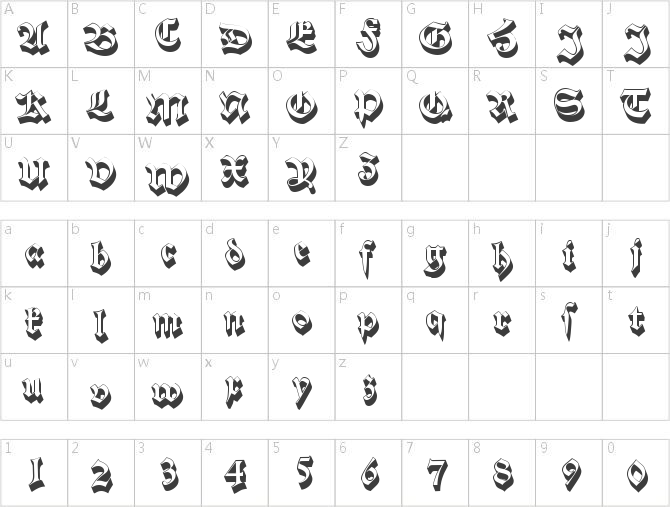
Alte Schwabacher Shadow URW
Alte Schwabacher Shadow URW介紹
Alte Schwabacher Shadow URW字體字庫是一款讓人賞心悅目、百看不厭的英文字體,適合各類廣告和產品包裝設計應用,字體大小0.09MB,格式為ttf字體,上傳用戶是文生電腦,作者/版權方為未知